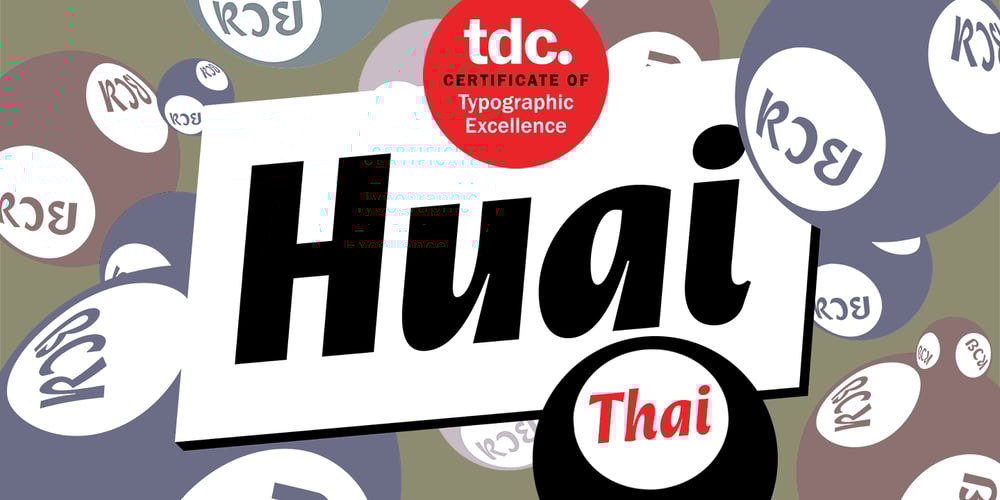
Huai Thai Font Family was designed by Potch Auacherdkul and published by Positype. Huai Thai contains 12 styles and family package options. หวยและหวยไทย ฟอนต์ที่ออกแบบโดยพชร์ เอื้อเชิดกุล ผลงานการออกแบบที่แสดงให้เห็นถึงการค้นคว้าใน 2 พื้นที่ที่ส่งผลซึ่งกันและกัน ระหว่างลายมือแบบตัวไทยที่เขียนกันทั่วไปและตัวละติน ผลที่ได้คือแบบตัวอักษร ‘หวย’ ที่ให้ความรู้สึกเป็นกันเองแต่มีความโดดเด่นชัดเจน มีลักษณะที่ไม่ขัดกับวิธีการเขียนที่คุ้นเคยและภาษาไทยที่เป็นต้นทางของแบบสำหรับตัวอักษรไทย ลักษณะของหัวสามารถแบ่งได้เป็น 2 ประเภท คือแบบมีหัวและแบบไม่มีหัว แบบมีหัวนั้นมีที่มาจากลักษณะการเขียนดั้งเดิมของตัวอักษรไทย ส่วนแบบไม่มีหัวนั้นเป็นการพัฒนาขึ้นมาใหม่เพื่อให้สอดคล้องกับแบบตัวละตินไม่มีเชิงฐาน (Latin sans serif typefaces) โดยในช่วงหลายปีที่ผ่านมา แบบตัวไทยไม่มีหัวนั้นได้รับอิทธิพลและค่อยๆ ปรับให้มีสไตล์สอดคล้องกับลักษณะของตัวละตินมากขึ้น มากจนถึงจุดที่เราสามารถนิยามแบบตัวไทยที่ได้รับอิทธิพลมานี้ว่า Thai Latinized ได้ ซึ่งความสงสัยต่ออิทธิพลที่เปลี่ยนแปลงไปนี้ เป็นเหตุของไอเดียในการพลิกมุมมองว่าอะไรจะเกิดขึ้นถ้าหากลายมือตัวไทยนั้นเป็นฝ่ายไปมีอิทธิพลกับแบบตัวละตินแทนผลลัพธ์ที่ได้ก็คือ โลกด้านกลับของแบบตัวไทยที่ถูกทำให้เป็นละติน ไม่ว่าจะเป็นป้ายหน้าร้านต่างๆ หรือริมถนนในกรุงเทพฯ การเขียนทั่วไปในชีวิตประจำวันที่เขียนอย่างเร็วๆ เป็นเส้นลายมือที่ลื่นไหล ทัังหมดนี้ส่งอิทธิพลให้เกิดรูปทรงของแบบที่เป็น DNA ของฟอนต์หวยชุดนี้ พัฒนาแบบด้วยการเก็บรายละเอียดและปรับธรรมชาติที่เป็นอยู่ของลายมือให้มีระบบมากขึ้น และต่อยอดขึ้นมาเป็นสัดส่วนต้นแบบของการพัฒนาฟอนต์ละตินที่เข้าคู่กับชุดฟอนต์หวยไทย ฟอนต์หวยนี้ได้นำส่วนสำคัญของตัวอักษรภาษาไทยถ่ายทอดไปสู่ตัวละติน พร้อมกับนำวิธีการ (ตลอดจนจิตวิญญาณ) ของการเขียนในช่วงเวลาปัจจุบันของคนไทยให้เข้ามาอยู่ในรูปทรงของตัวอักษรด้วย